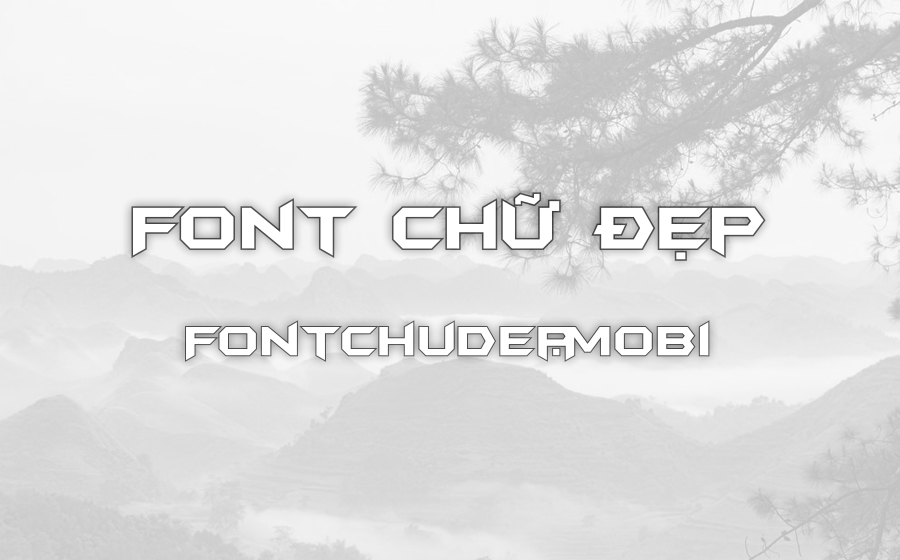
Font SVN Batman Forever Alternate Việt Hóa
SVN Batman Forever Alternate
Batman Forever Alternate là một font chữ mang tính biểu tượng, lấy cảm hứng trực tiếp từ logo nổi tiếng của bộ phim “Batman Forever” ra mắt vào năm 1995. Font chữ này thu hút sự chú ý bởi phong cách khoa học viễn tưởng đầy ấn tượng, thể hiện sự hiện đại và mạnh mẽ. Đây chắc chắn là lựa chọn tuyệt vời cho những thiết kế xoay quanh siêu anh hùng và công nghệ. Điều đáng chú ý là font chữ này đã được Việt hóa một cách tinh tế bởi Styleno.1 Fonts, đồng thời hỗ trợ nhiều ngôn ngữ khác, giúp nó trở nên dễ dàng tiếp cận và ứng dụng rộng rãi trên toàn cầu. Font này đã được đội ngũ từ FontChuDep.mobi tuyển chọn kỹ lưỡng và chia sẻ, nhằm đáp ứng nhu cầu của các nhà thiết kế và đem lại hiệu quả ấn tượng trong các dự án sáng tạo.
Nét độc đáo của Batman Forever Alternate nằm ở những đường nét góc cạnh và sắc sảo, tạo nên một tổng thể hiện đại, mạnh mẽ và đầy năng lượng. Font chữ này hoàn hảo cho các ứng dụng như thiết kế poster, tiêu đề phim, bìa sách, logo và nhiều dự án sáng tạo khác. Các ngành nghề có thể khai thác tối đa vẻ đẹp của font này bao gồm quảng cáo, giải trí và công nghệ. Nếu bạn đang tìm kiếm một font chữ có khả năng truyền tải cảm hứng vô tận và vẻ đẹp độc đáo, Batman Forever Alternate chắc chắn là một lựa chọn không thể bỏ qua.